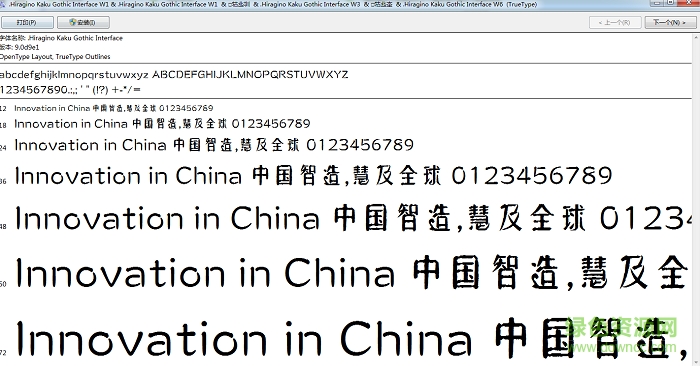
hiragino kaku gothic pron字體是一款有點小萌的字體,線條圓潤,結(jié)構(gòu)新穎,極具親切感,可以用在兒童主題的海報設計或用作相關(guān)廣告字體,喜歡小伙伴們快來下載吧!
字體造型生動活潑,有鮮明的節(jié)奏韻律感,色彩豐富明快,給人以生機盎然的感受。這種個性的字體適用于兒童用品、運動休閑、時尚產(chǎn)品等主題。